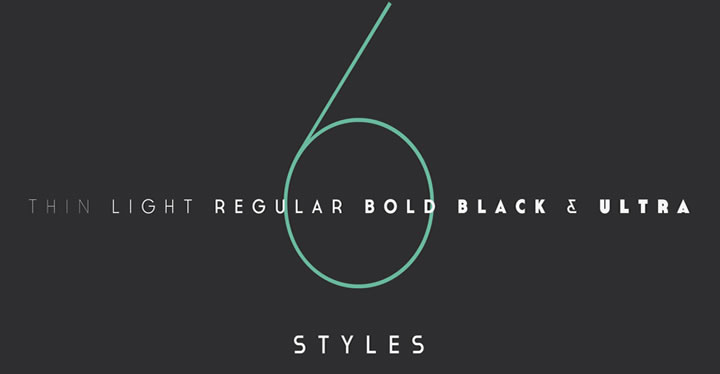
Typographie Gratuite : Cassannet plus !
Une bien belle typographie à télécharger pour vos créations ! Elle s’appelle Cassannet plus régular et elle s’adaptera parfaitement à des titres sur des affiches ou tout autres choix de votre part dans vos créations 🙂
En plus elle est déclinée en plein de graisses !